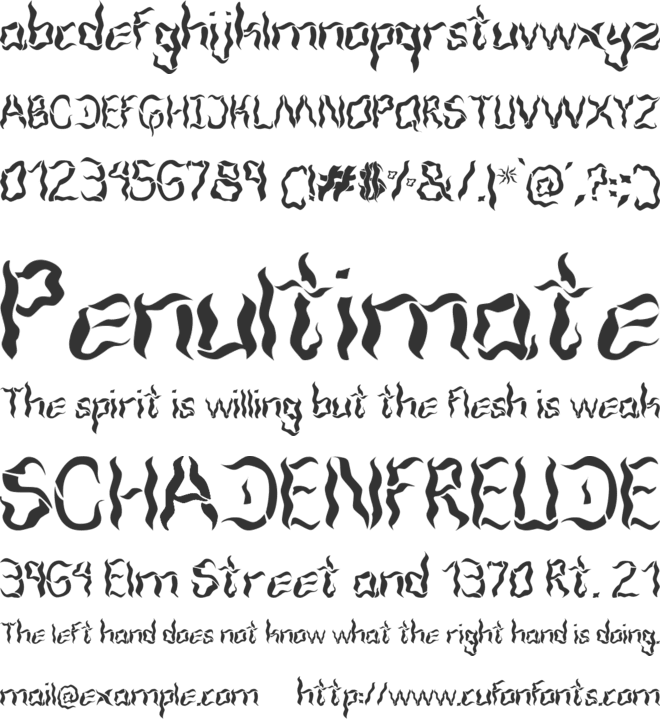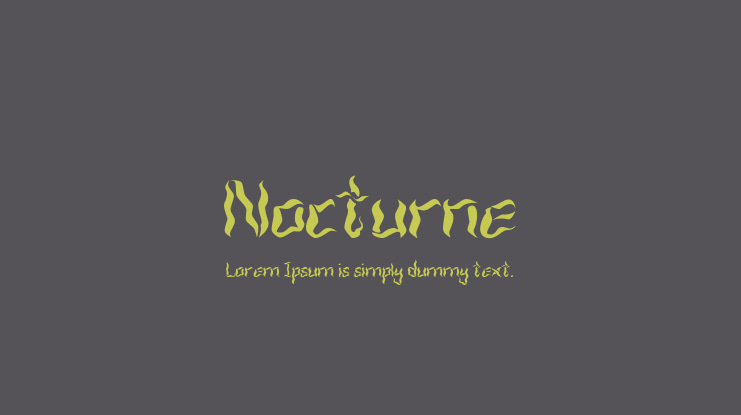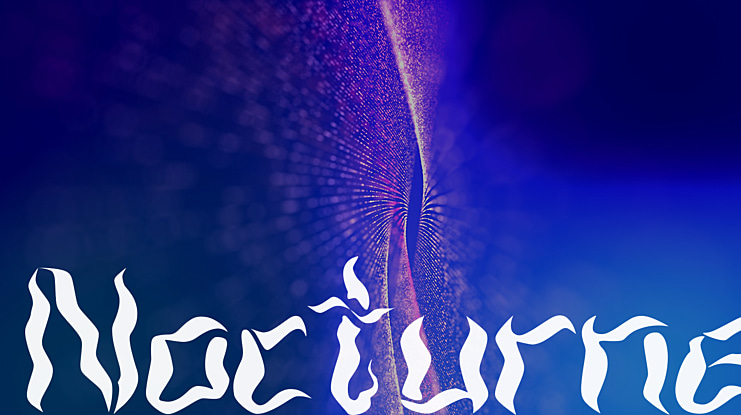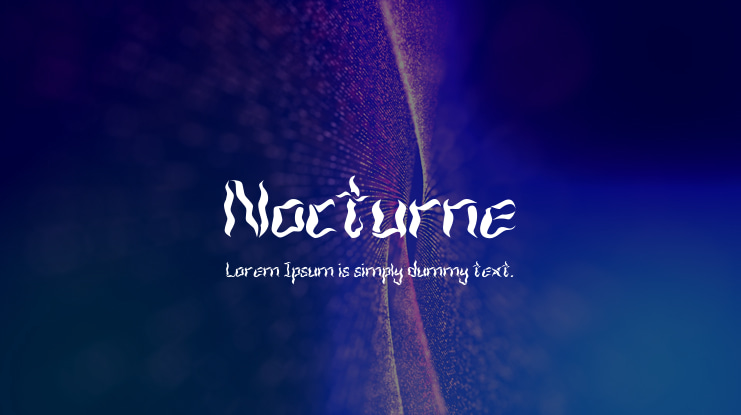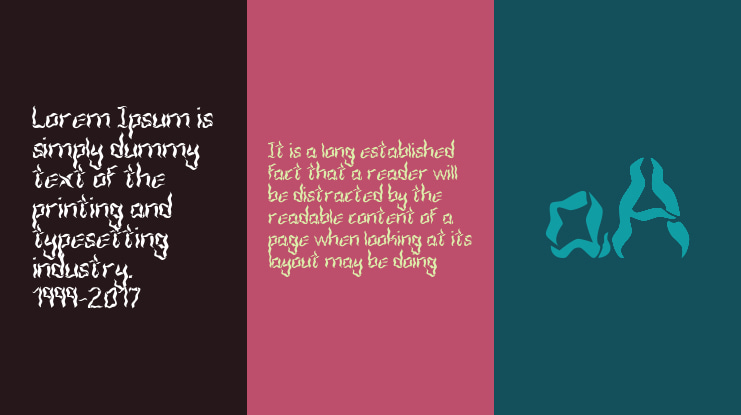
Nocturne Font
Danna Julieth Artunduaga Gantiva
Nocturne es una tipografía decorativa pensada de manera exclusiva para títulos cortos, debido a la cantidad de sus modulaciones y lo pesada que es debido a estas. No es recomendable usarla en menos de 42 puntos pues esta influye en su legibilidad.
Nocturne es una tipografía que puede ser utilizada para la creación de carteles, postales, anuncios, etc. con temáticas de terror, suspenso y/o ocultismo.
Inspirada en el movimiento de las ondas y de todo aquello que las posea, creando así un ambiente de suspenso y siendo llamativa debido a su movimiento.
Nocturne is a decorative typeface thought exclusively for short titles, due to the amount of its modulations and how heavy it it is due to these. It is not recommended to use it in less than 42 points as this influences their readability.
Nocturne is a typeface that can be used for creating posters, postcards, advertisements, etc. with horror themes, suspense and / or occultism.
Inspired by the movement of waves and everything that possesses them, thus creating a suspenseful atmosphere and being striking due to your movement.